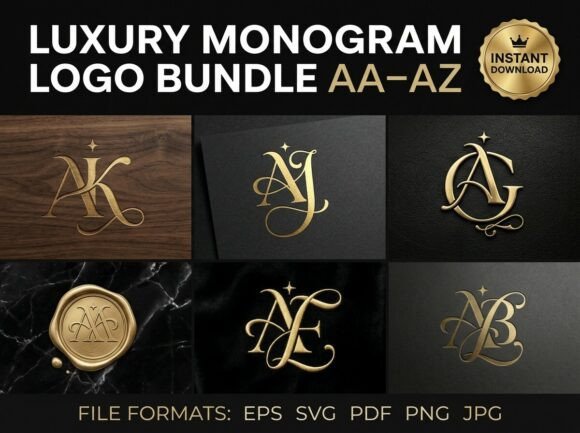
Luxury Monogram Logo Bundle AA–AZ
Si vous recherchez des ressources de haute qualité comme Luxury Monogram Logo Bundle AA–AZ, ce pack premium est un choix fantastique pour vos projets créatifs.
Conçu avec précision, Luxury Monogram Logo Bundle AA–AZ offre des vecteurs nets, une typographie fluide et une licence commerciale pour une tranquillité d'esprit.
Que vous créiez des produits POD (impression à la demande), des invitations de mariage ou des visuels pour les réseaux sociaux, Luxury Monogram Logo Bundle AA–AZ est un choix idéal.